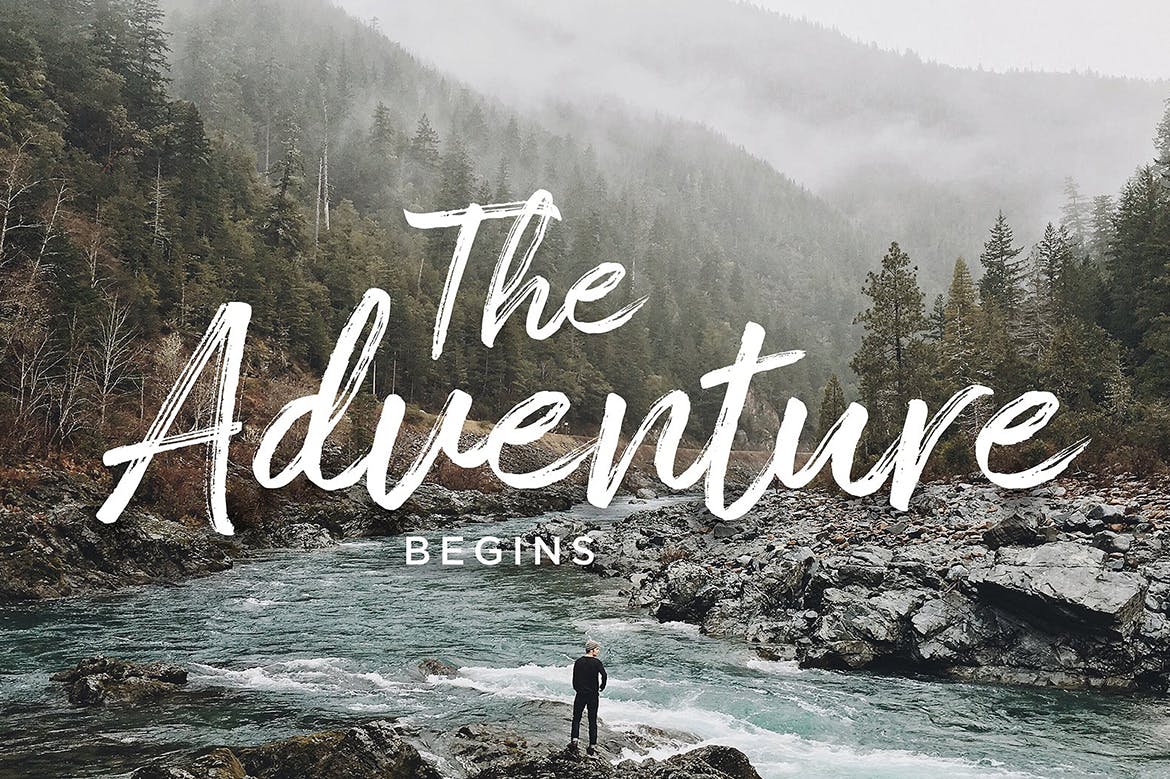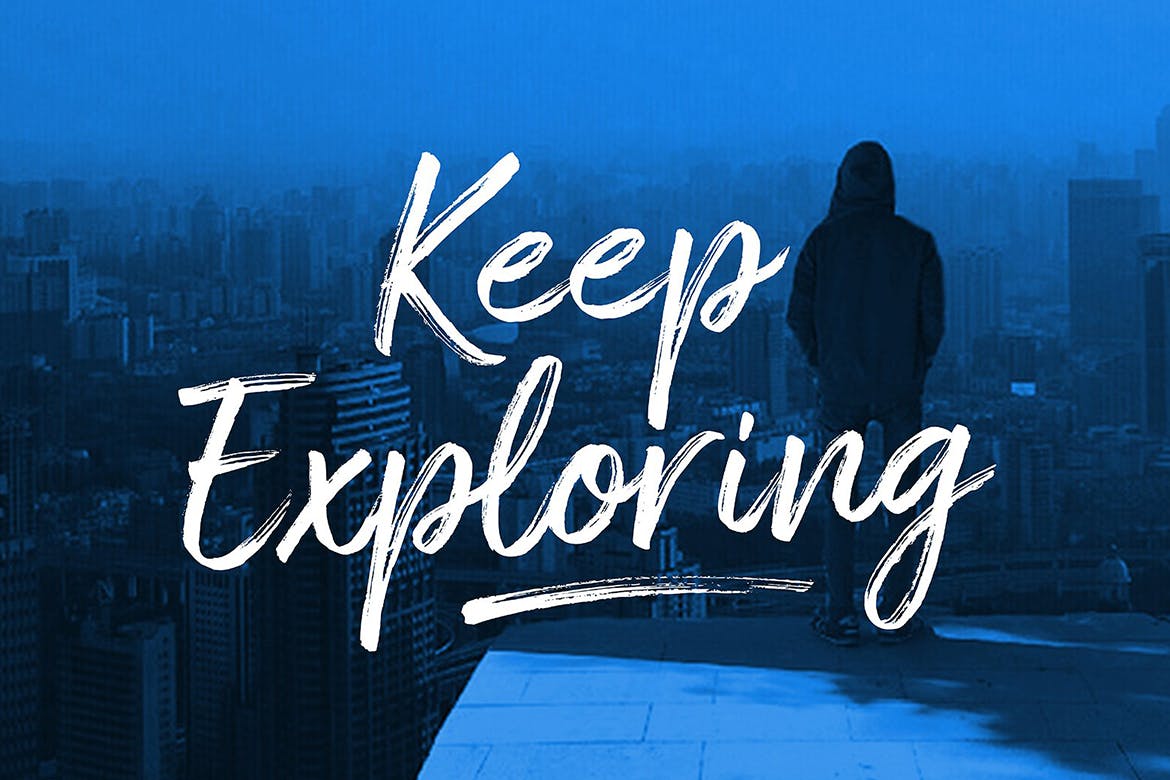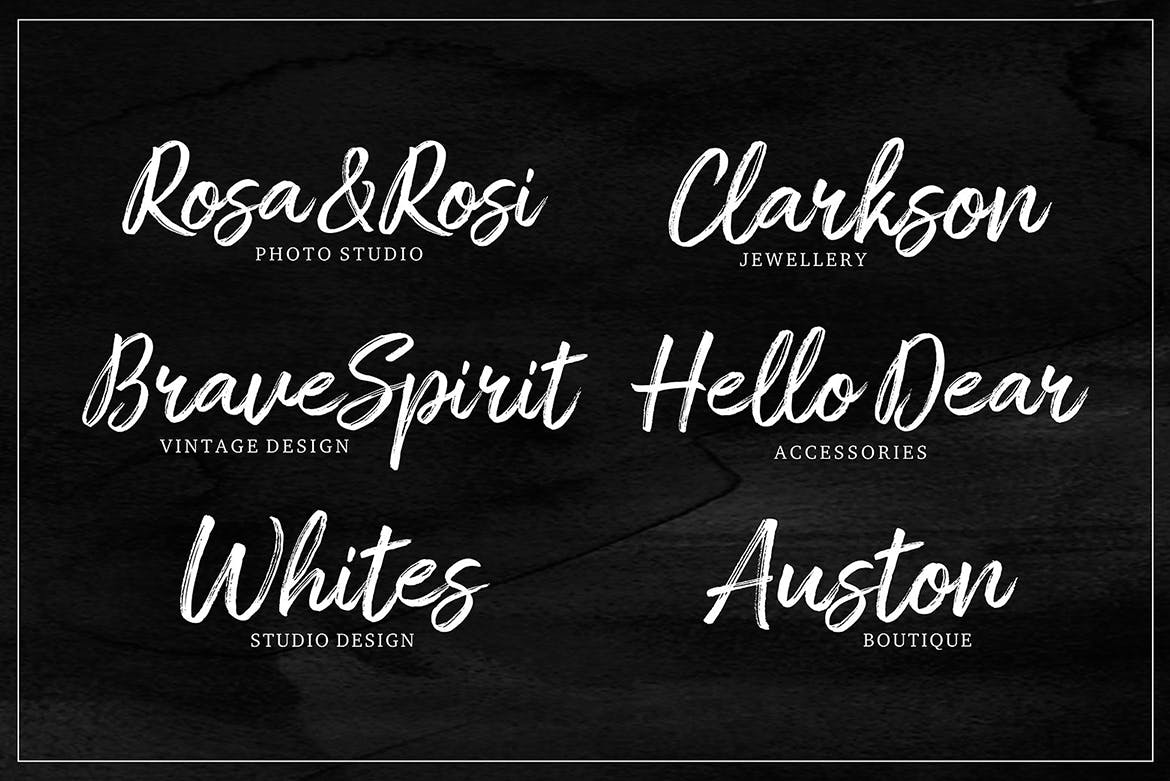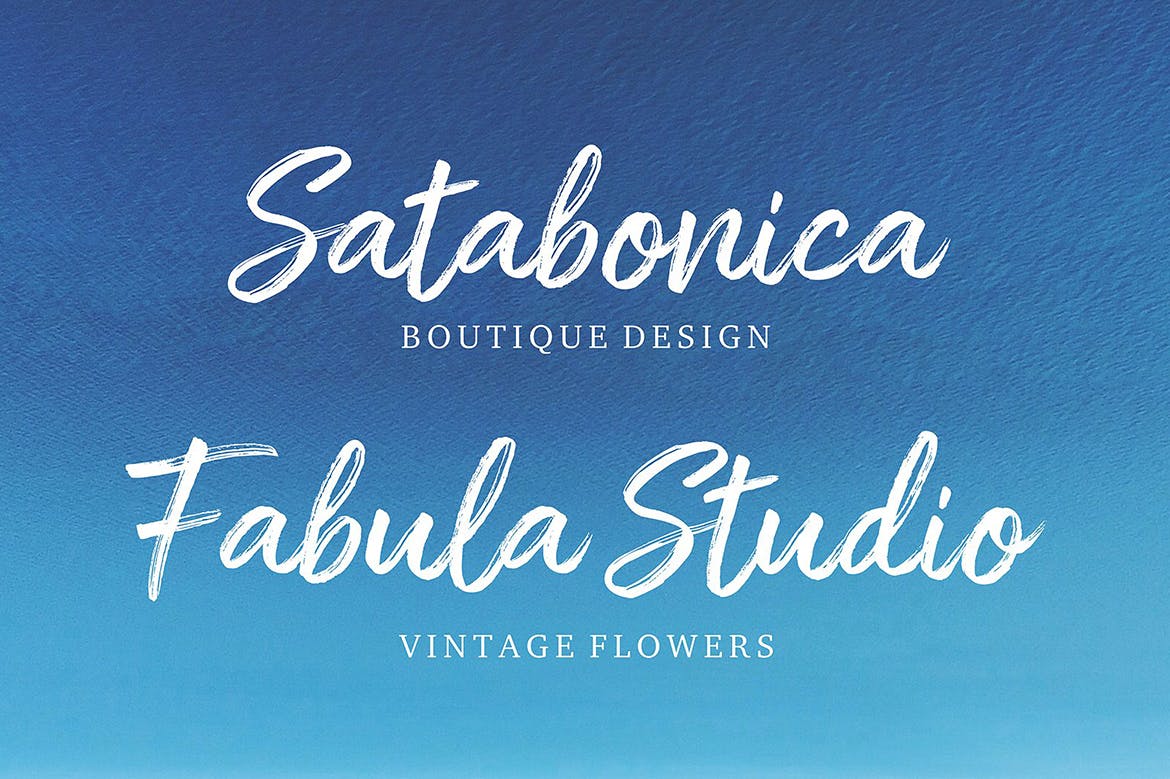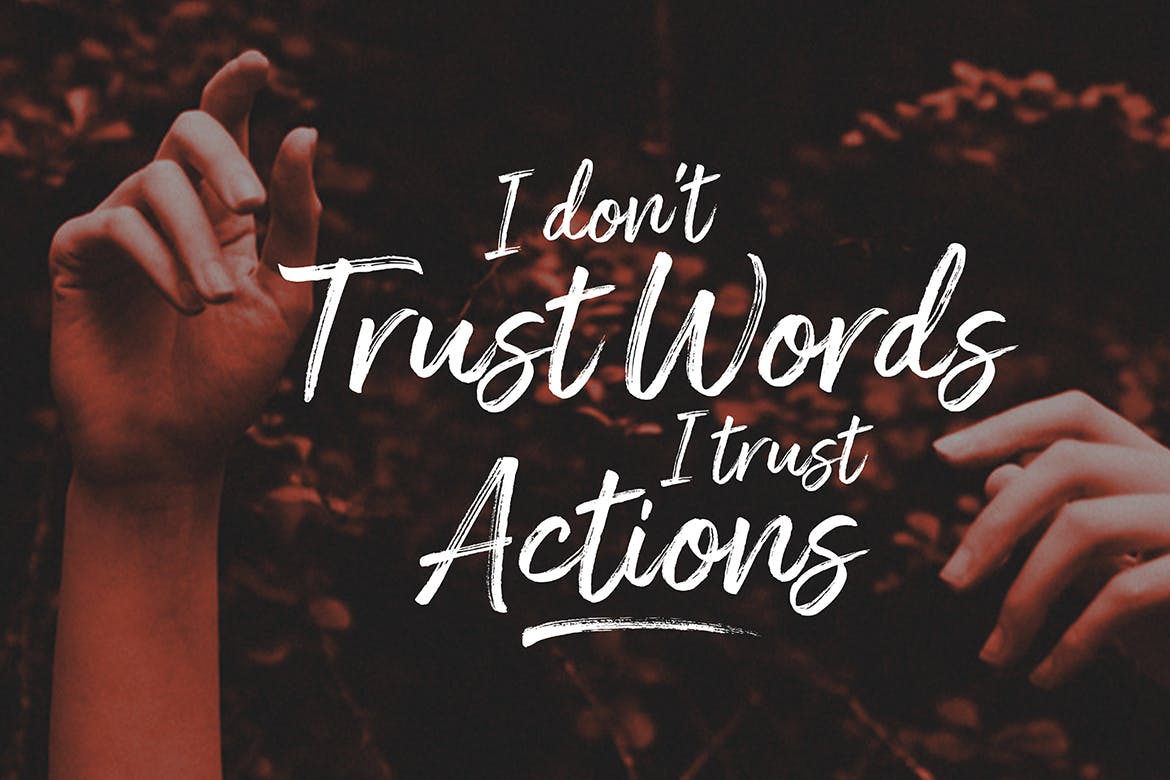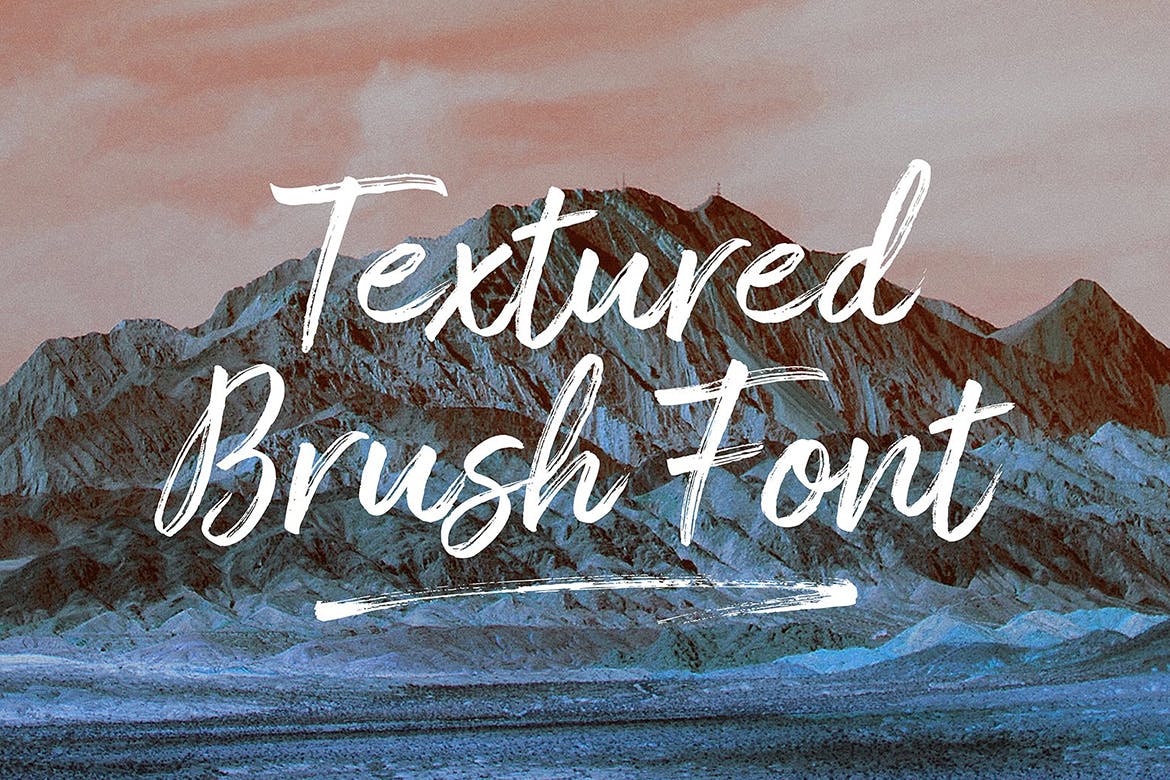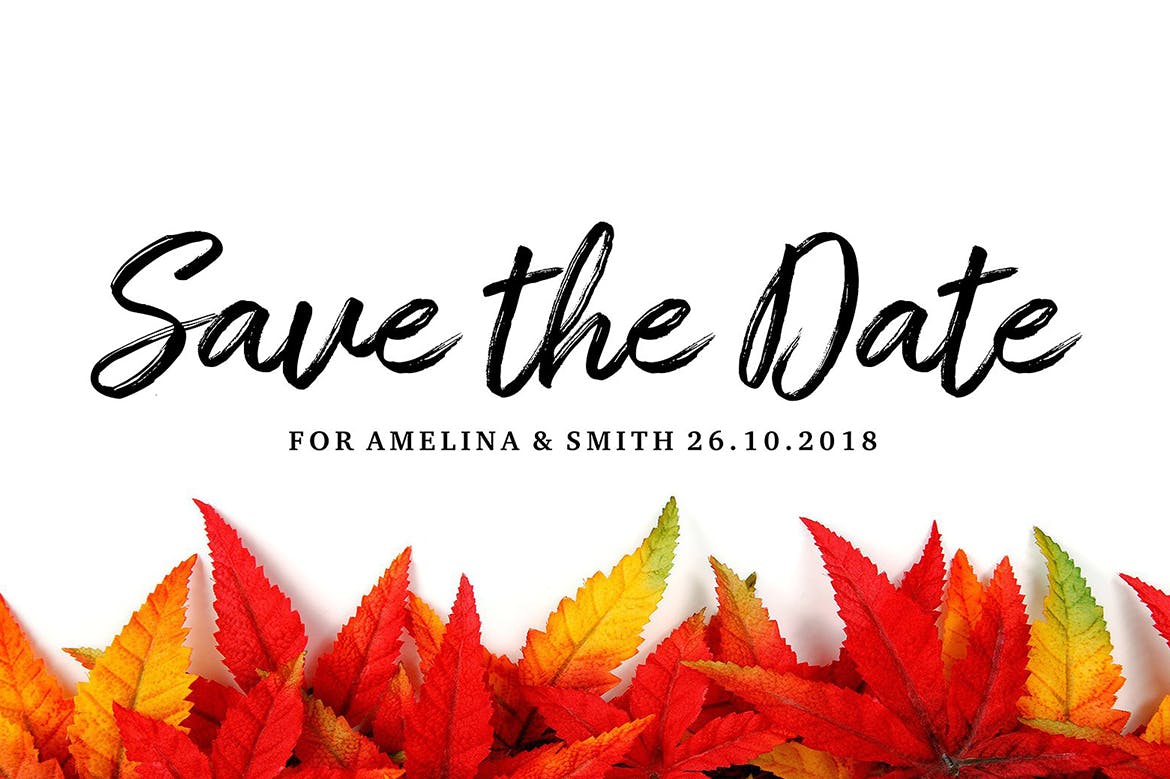
فونت آمیتن (Amithen) یک فونت برش با بافت منحصر به فرد است که با رویکردی مدرن به طراحی، به صورت دستساز و با خطکش نامنظم ایجاد شده است. این فونت برای استفاده در طراحی عناوین مناسب است و میتوانید از آن در طراحی لباس، دعوتنامهها، عناوین کتاب، طراحی ست اداری، نقل قولها، برندینگ، لوگوها، کارتهای تبریک، تیشرت، طراحی بستهبندی، پوستر و موارد دیگر بهره ببرید.
فونت آمیتن شامل مجموعه کاملی از حروف بزرگ و کوچک، پشتیبانی از چند زبان، اعداد، علائم نگارشی و لیگاتورها است.